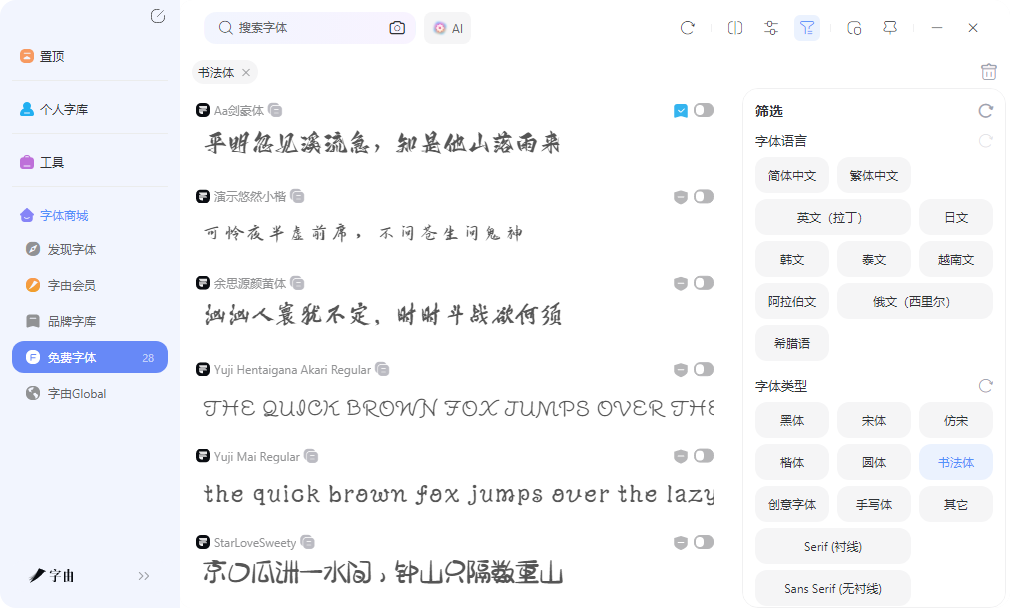
商务签名和个性风格都有,这几个签名生成器直接收藏
手写签名现在不止应用于实际,网页的电子签名用途也很广,不过手写签名潦草不专业,打印出来再手写再扫描更是折腾,扫描件往往模糊变形。电脑直接打字又显得冷冰冰,没有个人辨识度。现在有不少工具可以直接生成艺术化的签名,输入名字就能拿到带设计感的签名图片,插入合同或者电子文档里就能用。这篇文章整理的五个渠道,从中文特效签名到电子合同签署都有涉及。
签名的应用场景比较多样,合同文件需要正式稳重,品牌标识需要独特有辨识度,个人名片需要精致有设计感。字由的AI字体在生成签名图片时,可以根据不同场景选择不同风格的模板。而且生成流程也很简洁,打开网页版输入姓名,选择模板,大约二十多秒后拿到透明背景的PNG图片。插入Word文档时,图片悬浮在文字上方,不会破坏原有排版。做PDF合同封面时,把签名图放在标题下方,和正文形成视觉层次。
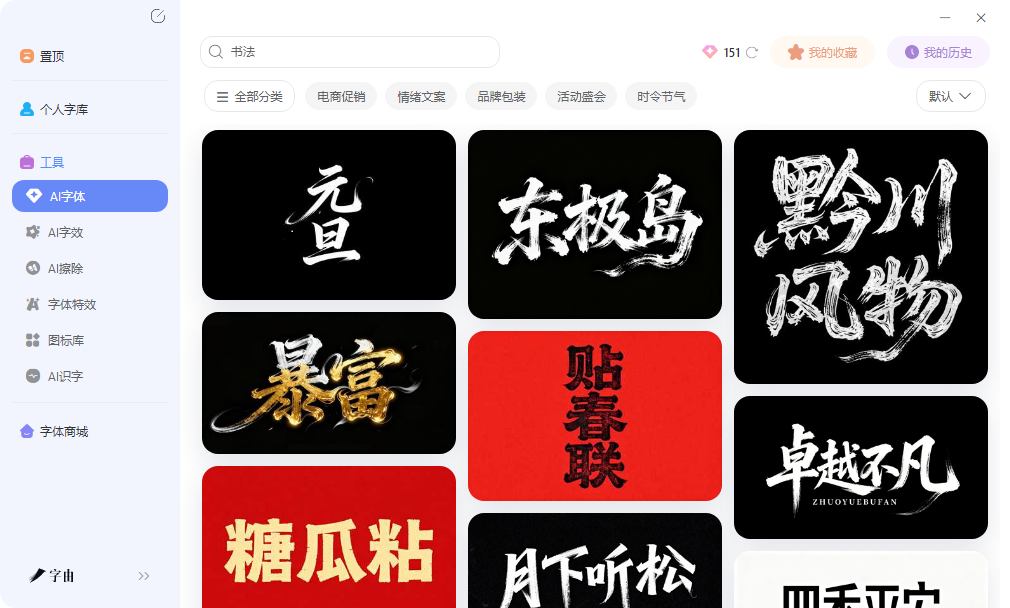
字体库里也有不少适合签名的资源。书法体分类下的行书和草书,笔画带有规范的运笔痕迹,适合做中式风格的正式签名。手写体分类下的现代手写体,笔迹自然流畅,适合做个人品牌标识或者文创产品签名。找的时候先点进对应分类,勾选免费商用标签,结果列表里就是允许商业使用的资源。预览框输入自己的姓名,调整到实际使用字号后查看效果,确认笔画清晰度再激活使用。
AI配字功能对签名场景也有帮助。有时候看到一张名片或者海报上的签名效果很好,想在自己的方案里用同款风格,但不知道是什么字体。上传参考图到AI配字,系统会分析画面的色调和气质,从字体库中推荐几款风格匹配的选项。推荐结果可以直接激活,在设计软件里立刻使用。这个功能在确认签名字体时比较实用,避免了自己凭感觉去找、结果找到的字体风格不对的情况。
签名的使用场景决定了工具选择。偶尔需要做几张中式风格的签名图,字由的AI字效配合书法体分类,从生成图片到激活字体都比较顺畅,作为艺术签名在线生成器的主力渠道比较实用。QuickAutograph适合快速获得手写风格签名,生成速度最快。SignatureGen.ai的AI定制程度最高,个性化空间最大。Jotform适合和表单流程整合,从生成到收集一站式完成。Docusign适合正式商务合同,法律效力最有保障。按自己的签名用途和合规需求来定即可。